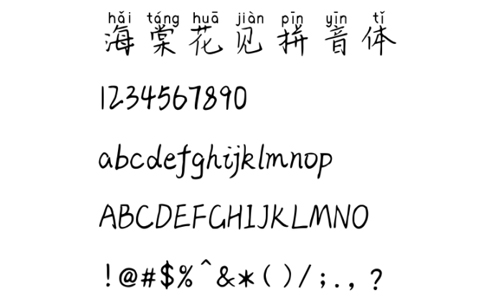
海棠花見拼音體字體是思雨字庫推出的硬筆手寫拼音體字體,美麗,只需要安靜的呈現(xiàn)。果實,只需要低調的奉獻。在不張揚的美里,體會一種靜雅的芬芳,又見海棠,又見你。本字體是在國家標準簡體字庫GB2312所包含6763漢字的基礎上,又增加了近200常用字,已經覆蓋了大陸99.75%的漢字使用頻率,足以滿足日常需求。歡迎喜歡海棠花見拼音體的朋友前來下載使用。